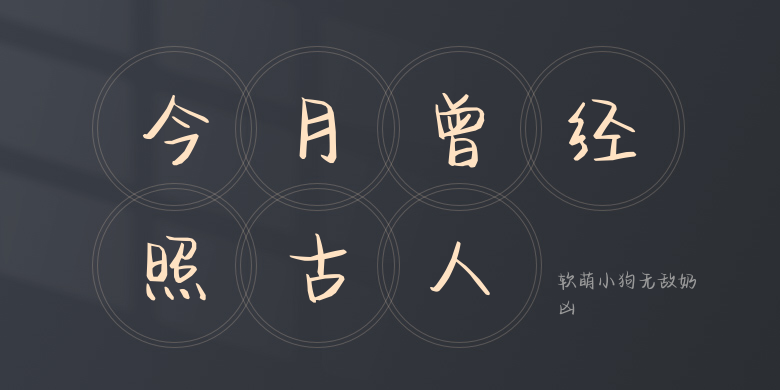
软萌小狗无敌奶凶
软萌小狗无敌奶凶,这款字体结构工整、笔画清晰,兼顾美观与易读性,适用于标题、正文、海报、包装、LOGO 等多种场景。字形优雅稳定,风格百搭耐看,适配日常排版与创意设计,让文字呈现更舒适、更具质感。软萌小狗无敌奶凶一笔一画,皆是细节,以均衡的比例、流畅的线条打造舒适视觉体验,字形端正大气,风格简约现代。无论是商业设计、品牌宣传还是日常排版,都能轻松驾驭,让文字更有格调与力量。软萌小狗无敌奶凶字体下载。